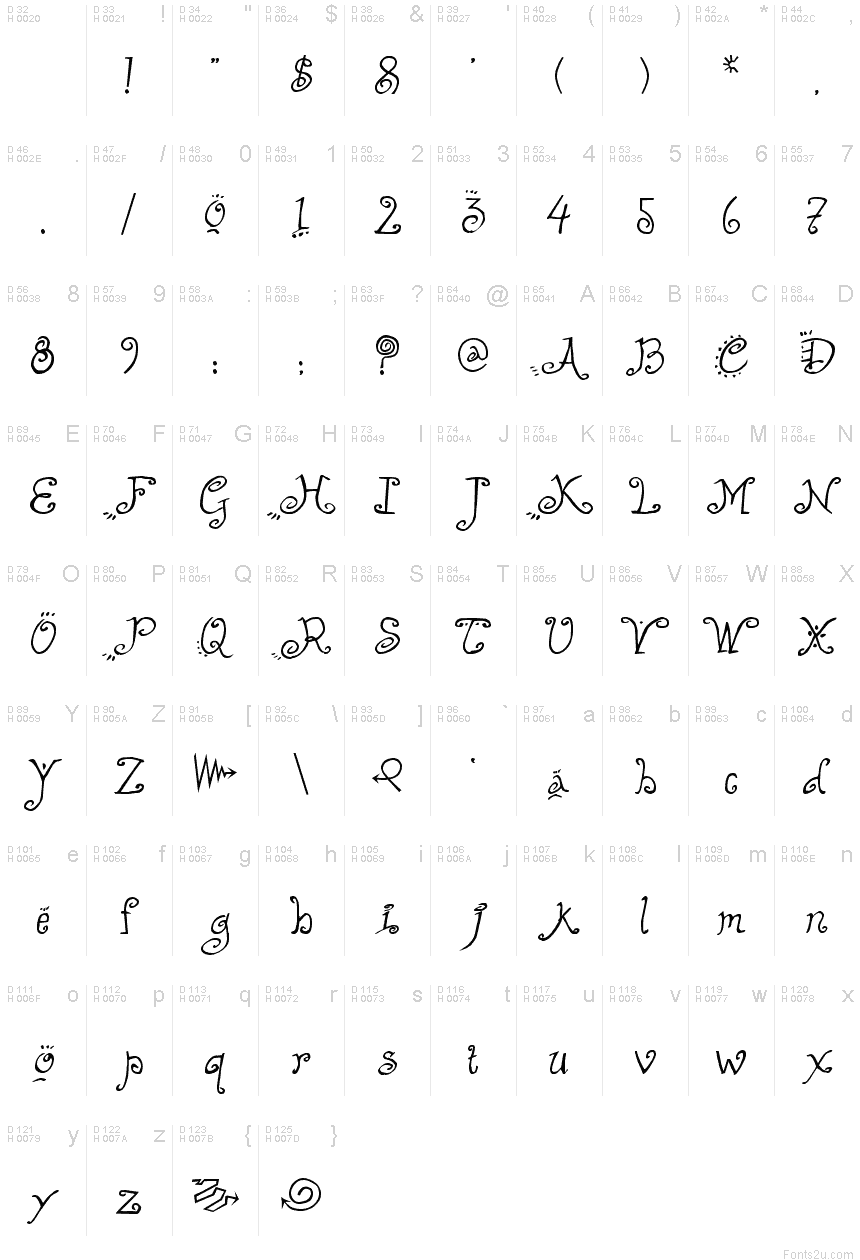
Helzapoppin autorstwa Davida F. Nalle’a to bezpłatny, odręczny krój dekoracyjny z figlarnym, baśniowym charakterem. Wysokie, pochylone litery wpadają w ciasne spirale, a zabawne kropki i akcenty wyglądają, jakby zostały nakreślone szorstkim piórem na starym pergaminie. Rytm jest swobodny, ale przemyślany, co nadaje nagłówkom poczucie zaczarowanego chaosu bez utraty czytelności.
Używając Helzapoppin, nadasz dziwacznej, teatralnej energii okładkom książek fantasy, plakatom o tematyce magicznej, zaproszeniom na Halloween, brandingowi cyrkowemu, grafikom do escape roomów, materiałom do gier RPG czy fantazyjnym menu kawiarnianym. Ten bezpłatny font zachwyca zwłaszcza w dużych rozmiarach, gdzie jego zawijasy i swashe mogą w pełni wybrzmieć; połącz go z czystym, neutralnym krojem bezszeryfowym w tekście głównym, aby zachować równowagę i przejrzystość układu.